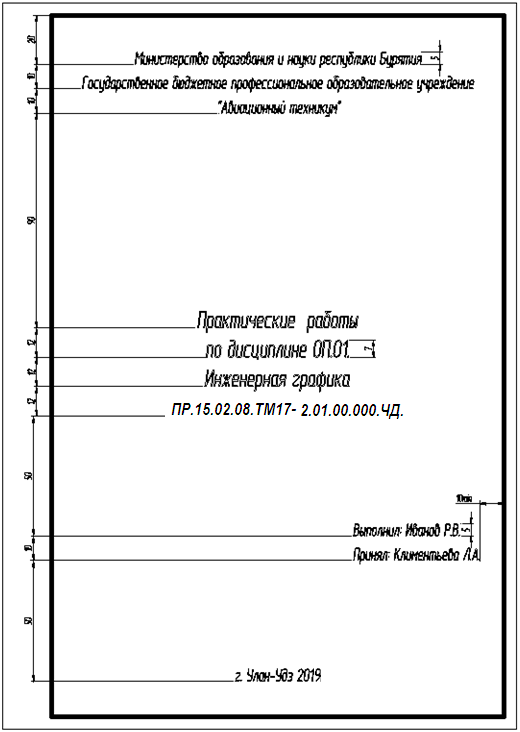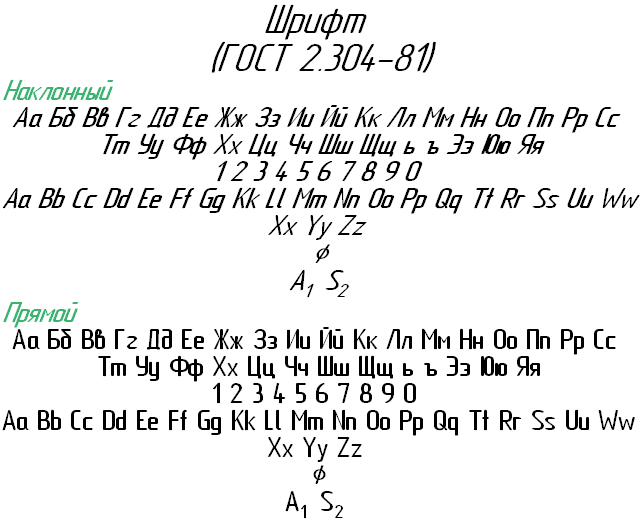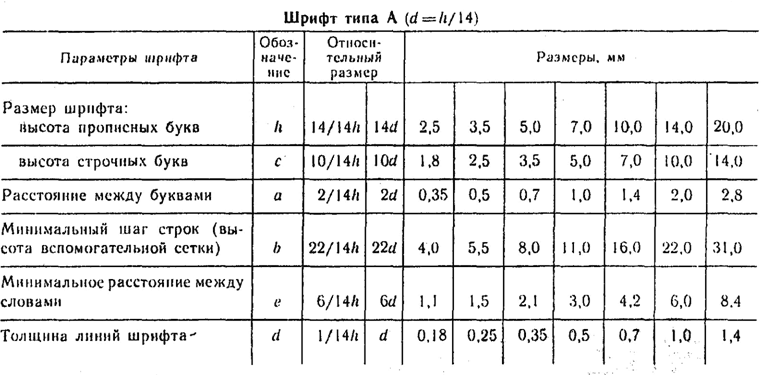
Учебная цель: Научиться выполнять шрифты чертежные, разработать титульный лист для практических работ.
На формате А4 выполнить титульный лист для практических работ по дисциплине «Инженерная графика». ГОСТ 2.304-81 «шрифты чертежные» тип А.
Рисунок 1 Образец готовой работы
Краткие теоретические и учебно-методические материалы по теме практической работы.
ГОСТ 2.304–81 « Шрифты чертёжные» устанавливает правила выполнения шрифтов, которые наносятся на чертежи и другие документы всех отраслей промышленности. Стандарт устанавливает следующие основные размеры шрифтов: 2,5; 3,5; 5; 7; 10; 14; 20; 28; 40. Размеры шрифтов определяются высотой (h) прописных (заглавных) букв в миллиметрах. Эта высота измеряется по направлению, перпендикулярному к основанию строки. Высота строчных букв (с) определяется из отношения их высоты (без отростков) к размеру шрифта (h). Цифры, встречающиеся в тексте, должны иметь высоту прописных букв. Толщина линии шрифта обозначается буквой d и определяется в зависимости от типа и высоты шрифта.
Рисунок №2
1. Шрифтом называется графическая форма изображения...
1) букв, цифр и условных знаков
2) только букв
3) только букв и цифр
2. Выполнение шрифтов устанавливает ГОСТ:
1) 2.301-68*
2) 2.104-68*
3) 2.304-81
3. Надписи на конструкторских документах выполняют чертежными шрифтами следующих видов:
1) без наклона к основанию строки
2) с наклоном под углом 70 градусов
3) с наклоном под углом 75 градусов
4. Размер шрифта обозначается буквой...
1) q
2) h
3) d
5. Для шрифта типа А толщина линий букв и цифр равна...
1)1/14h
2) 1/10h
3) 1/8h
6. Для шрифта типа Б толщина линий букв и цифр равна...
1) 1/14h
2) 1/10h
3) 1/8h
7. Сколько размеров шрифтов в соответствии со стандартом используется?
1) 6
2) 8
3) 10
8. Сколько прописных букв русского алфавита имеют одинаковые начертания с одноименными строчными буквами?
1) 15
2) 16
3) 17
9. Какой буквой обозначается толщина линий шрифта?
1) d
2) e
3) h
10. Какой буквой обозначается высота строчных букв?
1) d
2) e
Разметить линии для текста. Линии можно разметить чернографитным карандашом твердость Т или иглой циркуля.
Написать текст по образцу ГОСТ 2.304-81 «шрифты чертежные» тип А номер шрифта 7 и 5.